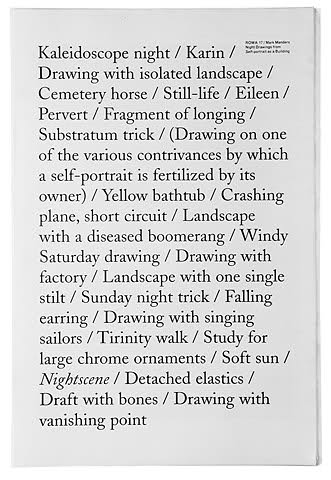
Um welche Schrift handelt es sich hier ?
Hi, ich hab hier eine ganz schöne Schrift gefunden:
vielleicht weiß jemand wie sie heißt ?
leider ist die Auflösung etwas zu schlecht um genaueres zu sagen. Die Serifen sind nicht genau zu erkennen. Ich würde da auf eine Caslon als Verdächtige tippen. Nah ran kommen z.B. Adobe Caslon Pro, Caslon Old Face und LTC Caslon. Hast Du die Grafik in höherer Auflösung?